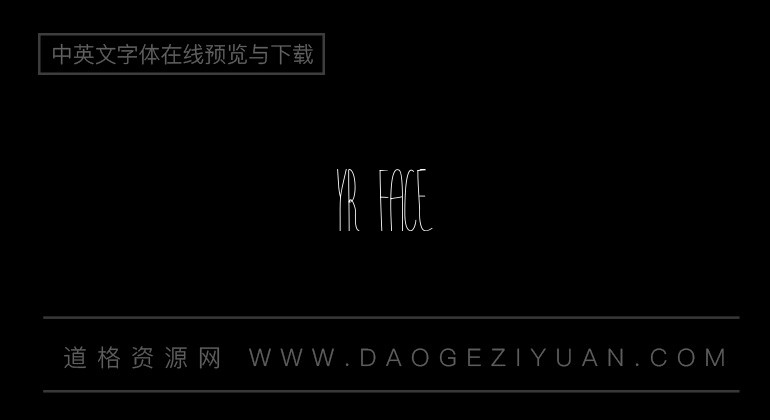
Yr Face
Yr Face 是一款由美国字体设计师 Jason Kottke 所设计的无衬线字体,它非常简洁明了,拥有简单的线条,具有平衡感,可以应用于多种语言。此字体特别适合用于网页设计,比如标题、标签、按钮等,也适合用于报纸、杂志、书籍、海报等印刷品的设计。Yr Face 字体的字符比较简单,但又有趣,可以给设计师提供更多的创意空间。
Yr Face是一款非常不错的手写艺术字体,具有很好的视觉感,适合于文化类的宣传设计、商业类品牌的广告和产品包装设计以及个性化文字排版等较多场景。